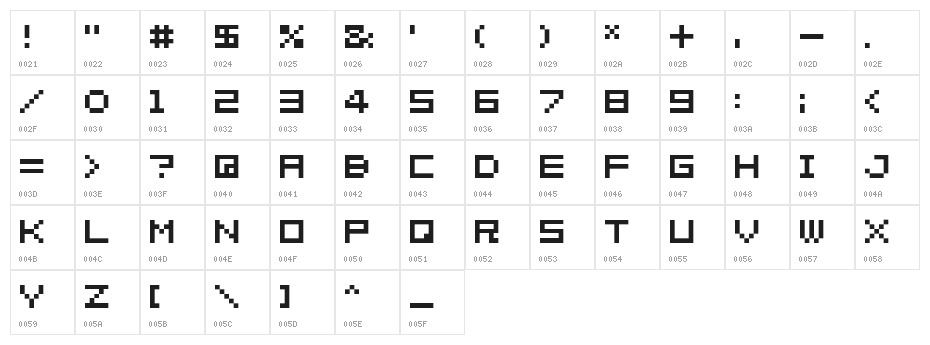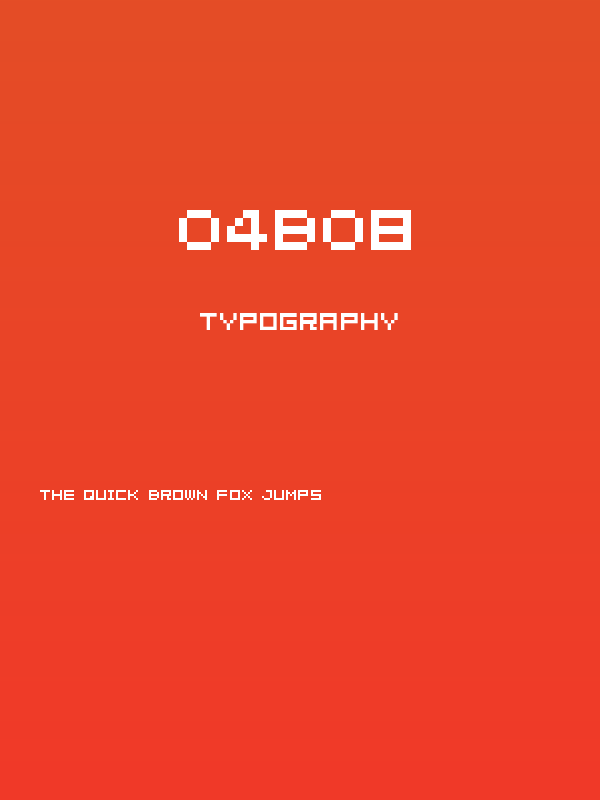
04b08 Font
| Categorie | Pixel |
| Stile generale | Retro, Digital |
| Caso d'uso | Headlines, Logos, Digital Art |
| Progetti proposti | Ideal for retro video game designs, digital art projects, tech-themed posters, and any creative work that seeks to evoke a nostalgic digital aesthetic. |